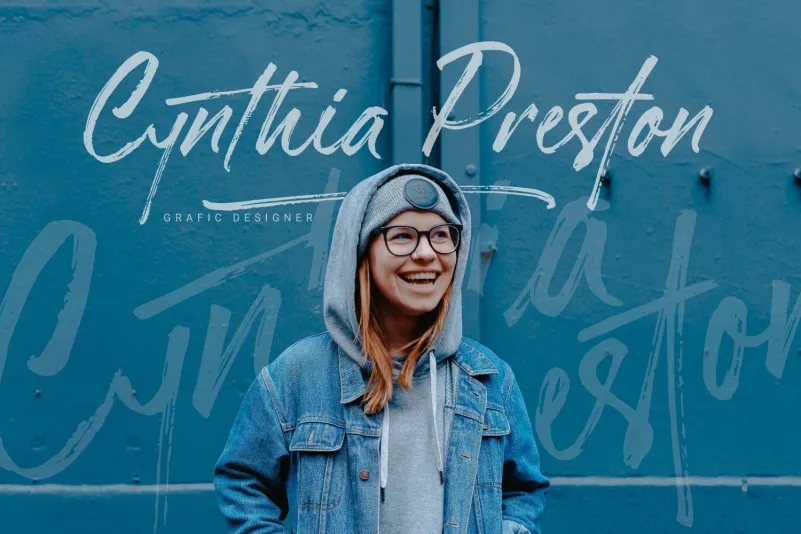
Hillstone Font – Fonte Grátis
Hillstone Font
A Hillstone Font é uma fonte que retrata com precisão a experiência física do autografoado. Feita por meio de raspagens fortes e rápidas feitas na argila suja com um traço de caneta, essa técnica criou uma textura irregular que define o estilo da fonte. Com uma aparência desgastada e áspera, a Hillstone Font é ideal para quem busca um estilo brush que transmite personalidade e vigor. Sujeita à mão, esta fonte é perfeita para ambientes gráficos que exigem simpatia e autenticidade. Criado pelo designer 38.lineart, o resultado é uma combinação de arte e tecnologia, uma expressão visual cheia de vida. Hillstone Font é um esforço meticuloso em capturar o espírito de criação manual. Em cada traço, palpamos a mão dos artistas que criaram essa fonte única, fazendo com que você se sinta ligado ao processo artesanal por trás dela. Sujeito a uma variedade de ambientes gráficos e formatos de mídia, a Hillstone Font oferece uma perspectiva visual vibrante e autêntica para sua próxima peça de design.
Designer: 38.lineart